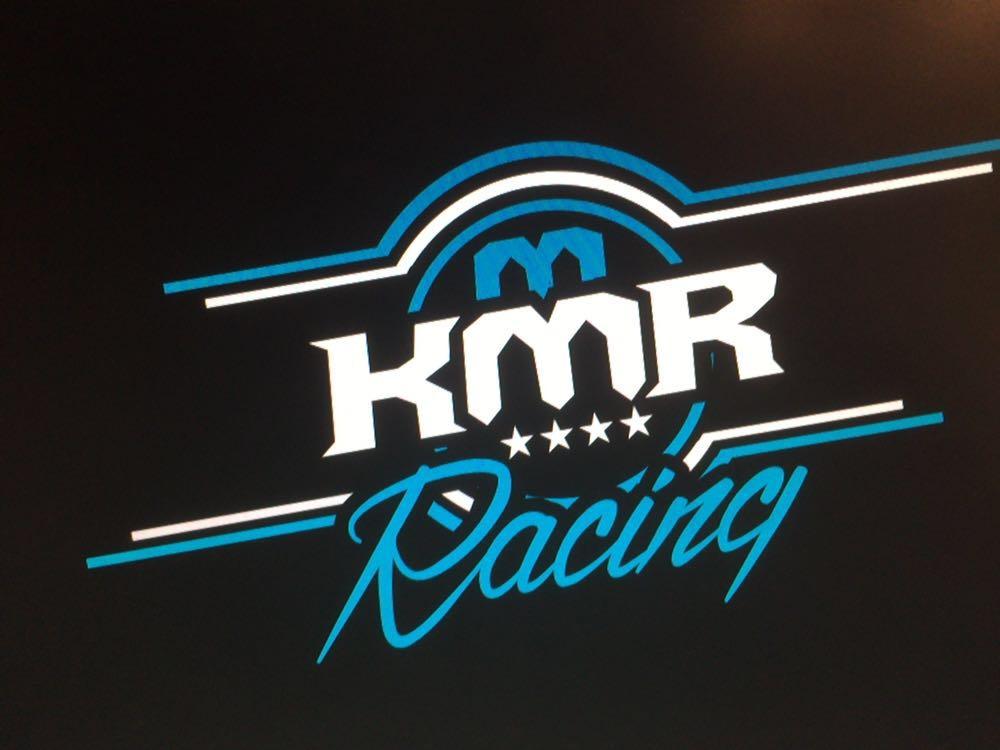
Welche Schriften? (KMR)
ich brauche mal wieder Hilfe habt Ihr ne Idee welche Schriften das sind?
So unakkurat, wie dieses KMR da aussieht, ist das mit an Grenzen sichernder Wahrscheinlichkeit selbst gebastelt. Bestenfalls "Racinq" könnte n Font sein.
"Racing" ist aus der Ventilla Script, free for personal use